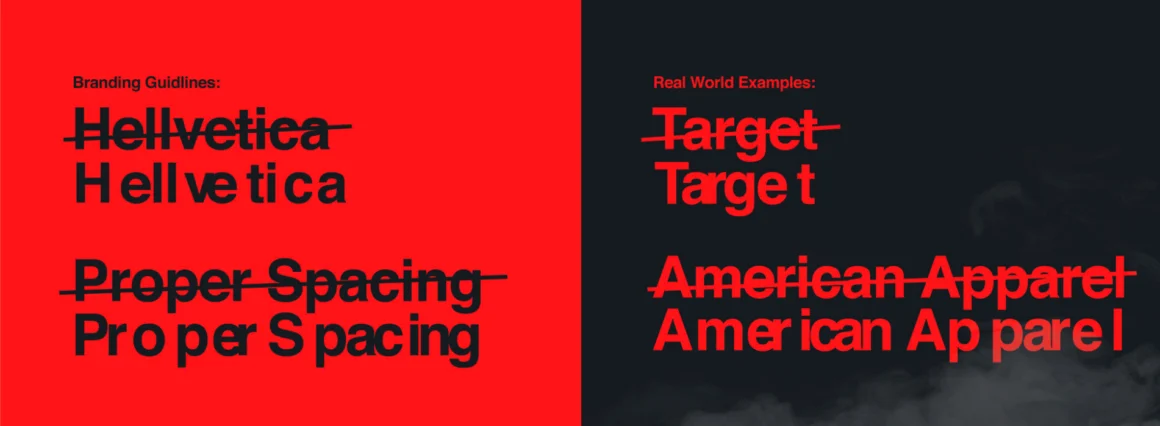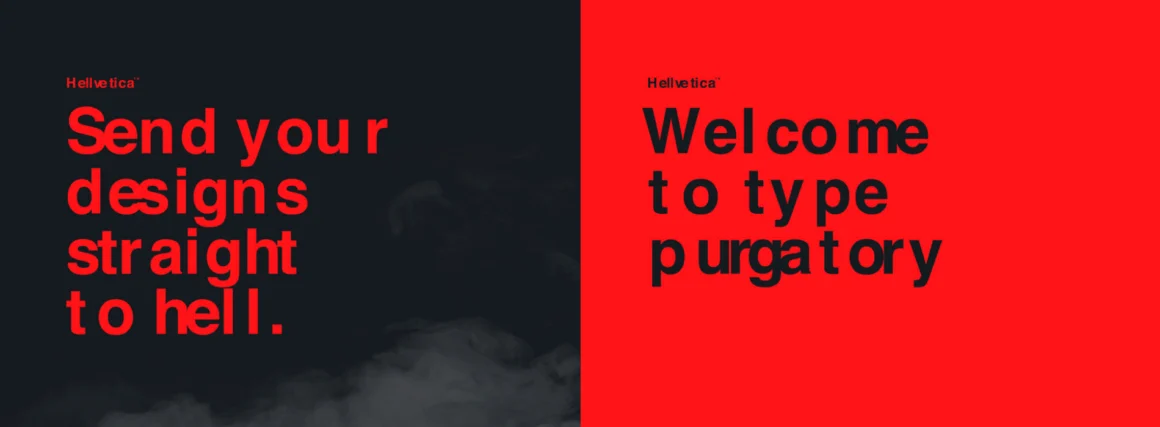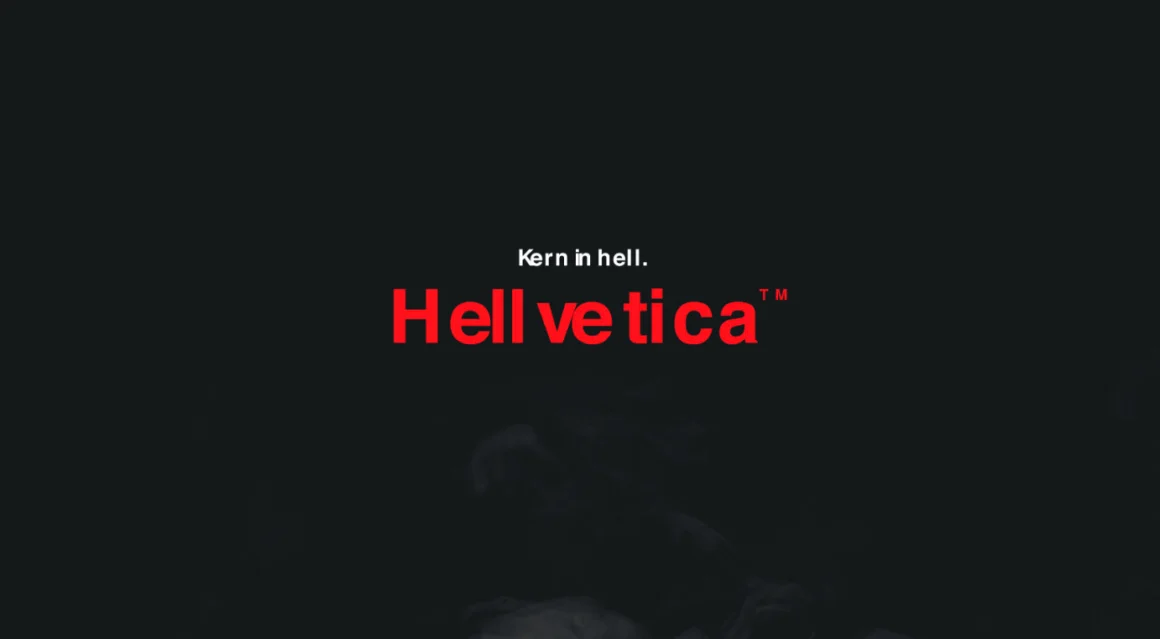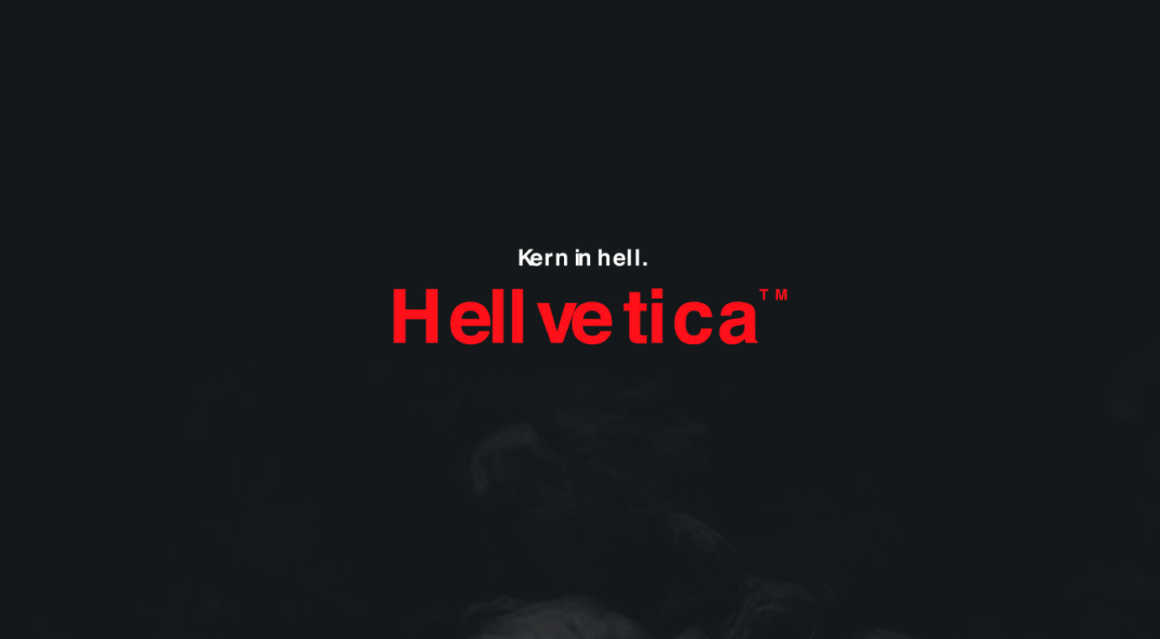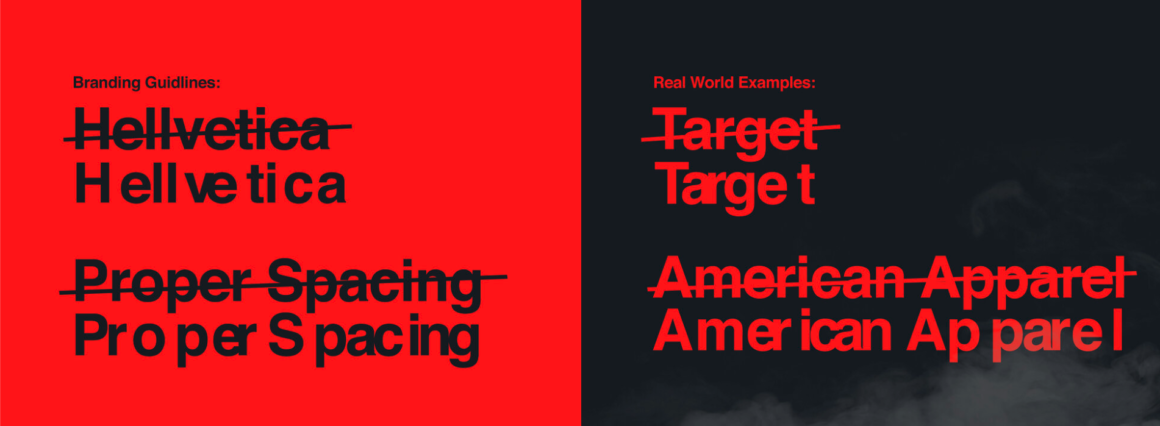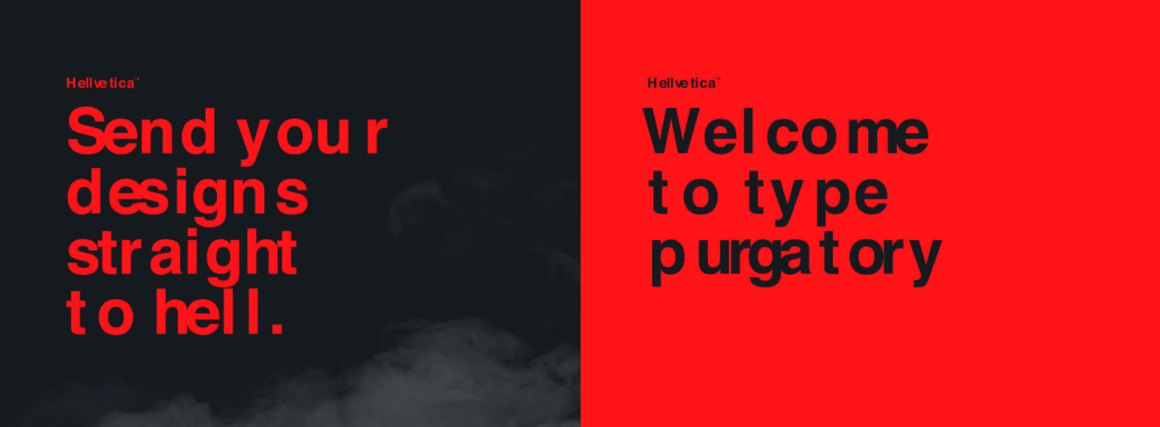
Pour Halloween, ces créatifs ont créé Hellvetica, une typo démoniaque
Vous connaissez tous Helvetica, cette typographie légendaire adorée par les créatifs pour sa simplicité et sa beauté. Et bien deux créatifs de l’agence R/GA ont décidé de la rendre un peu plus démoniaque pour Halloween 2019.
C’est une actualité plutôt cool que je vous partage aujourd’hui et qui devrait faire plaisir aux créatifs et copywriters. Il fallait y penser et Zack Roif et Matthew Woodward l’ont fait : détourner la célèbre typographie Helvetica en Hellvetica. Et le principe n’a pas besoin d’être expliqué car il saute directement aux yeux.
En effet, cette nouvelle typographie vous emmène tout droit en enfer grâce à sa déstructuration qui va faire pâlir vos clients. Elle reprend la célèbre typographie tout y ajoutant une petite touche de folie. Certains diront qu’elle est ivre, d’autres diront qu’elle est habitée par Satan. Dans tous les cas, c’est clairement cette typo qu’il faudra utiliser cette année si vous voulez faire un carton pour Halloween.